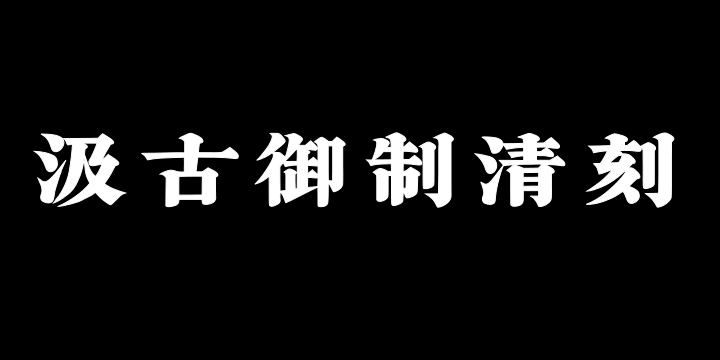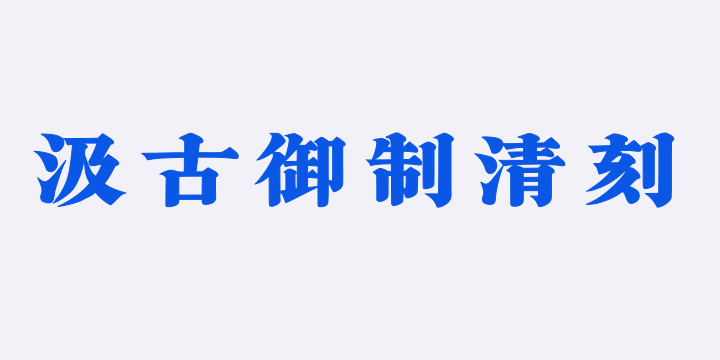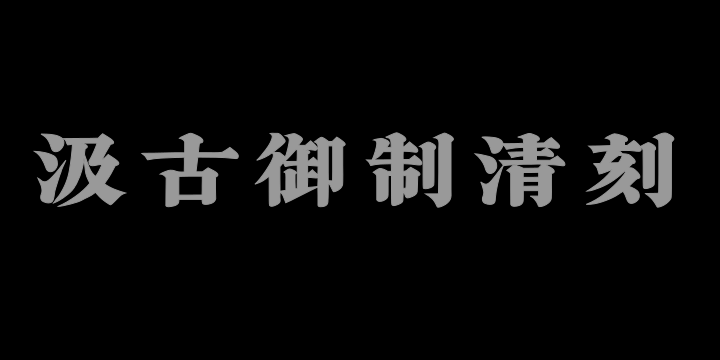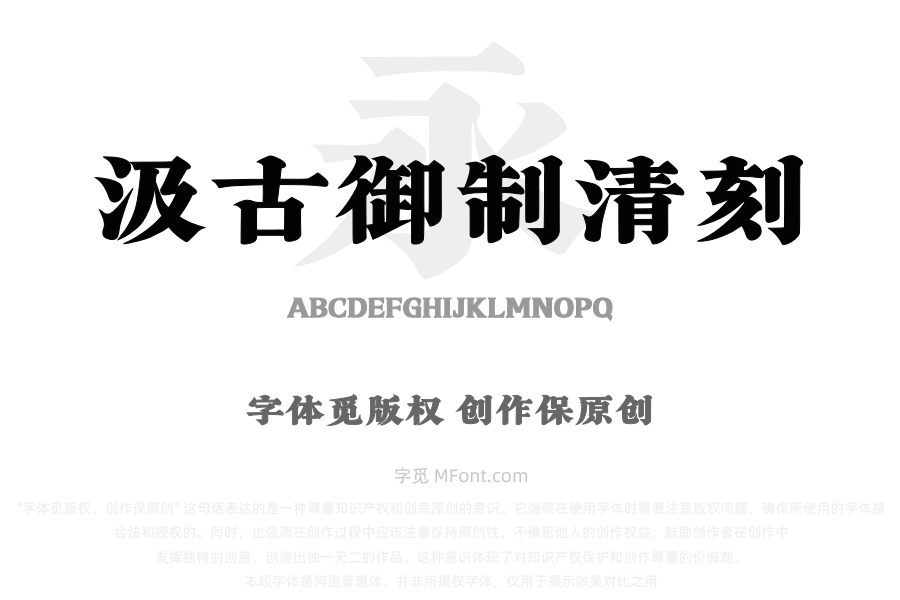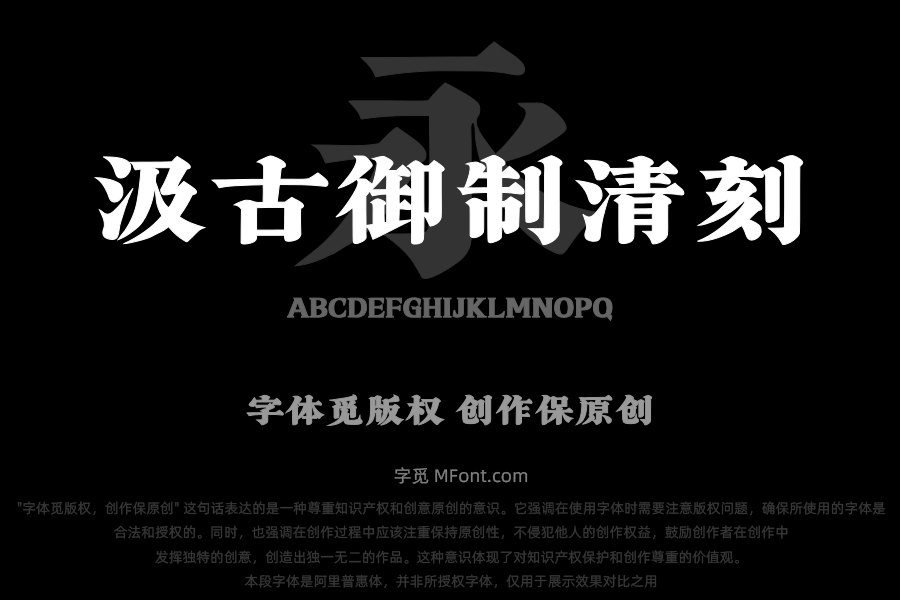
关于山海汲古御制清刻W字体字库信息
字体全名: 山海汲古御制清刻W
铸字厂: 山海字库
设计师: 山海字库
字体简介: 山海汲古御制清刻,是一款国风复古刻本字体,包含简繁汉字9169个。字形秉承中国明代古籍善本之字形特性,版刻刀法剔透,字形方正,端庄严谨,古朴大方,起落顿笔有棱角。在饱有笔墨之意的同时,又突显刀刻之锋美,笔刀结合刚柔并济。在秉承笔形间创新,结合当代设计视觉环境,融入现代审美,适用场景更多元,笔画造型清晰锐利,删繁取简,笔锋凌厉,速度感强,粗细对比强烈,重现刀刻古韵之美。